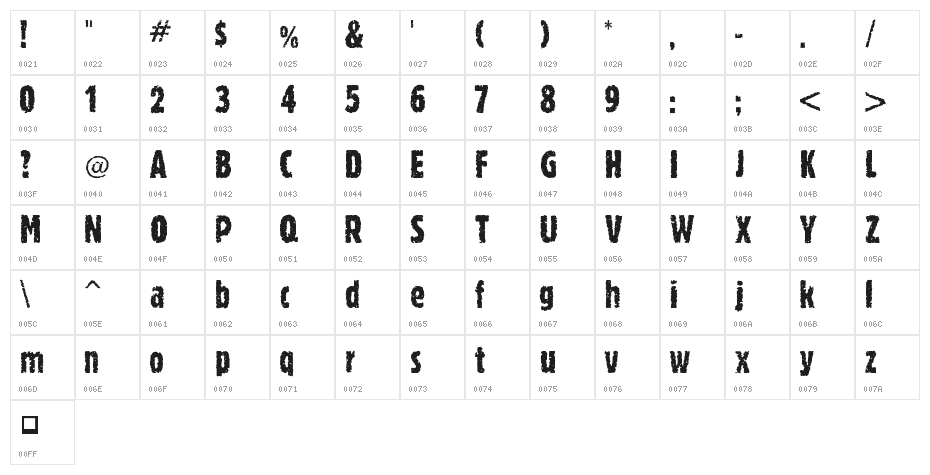
Romeo Font
✎ Broken
| Progetti proposti | Ideal for posters, album covers, branding for edgy products, or any design needing a vintage or grunge aesthetic. |